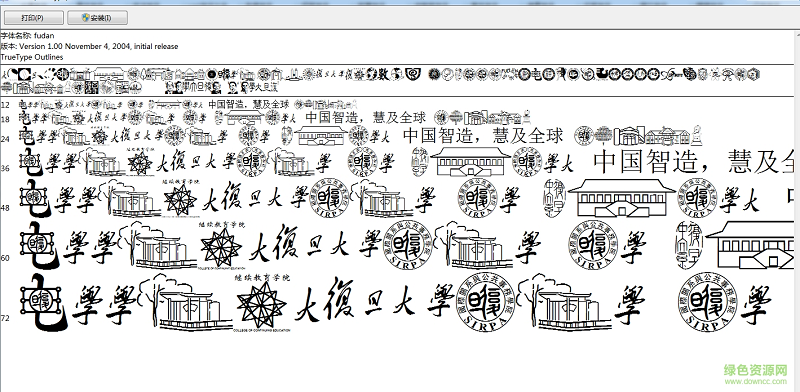
復(fù)旦體字體
復(fù)旦字體是一款針對復(fù)旦大學(xué)而推出的一款藝術(shù)字體,字體帶有復(fù)旦校徽、標(biāo)志等,大學(xué)人文氣息相當(dāng)濃厚,特別適合學(xué)校相關(guān)設(shè)計領(lǐng)域!有興趣的朋友就來綠色資源網(wǎng)下載吧。